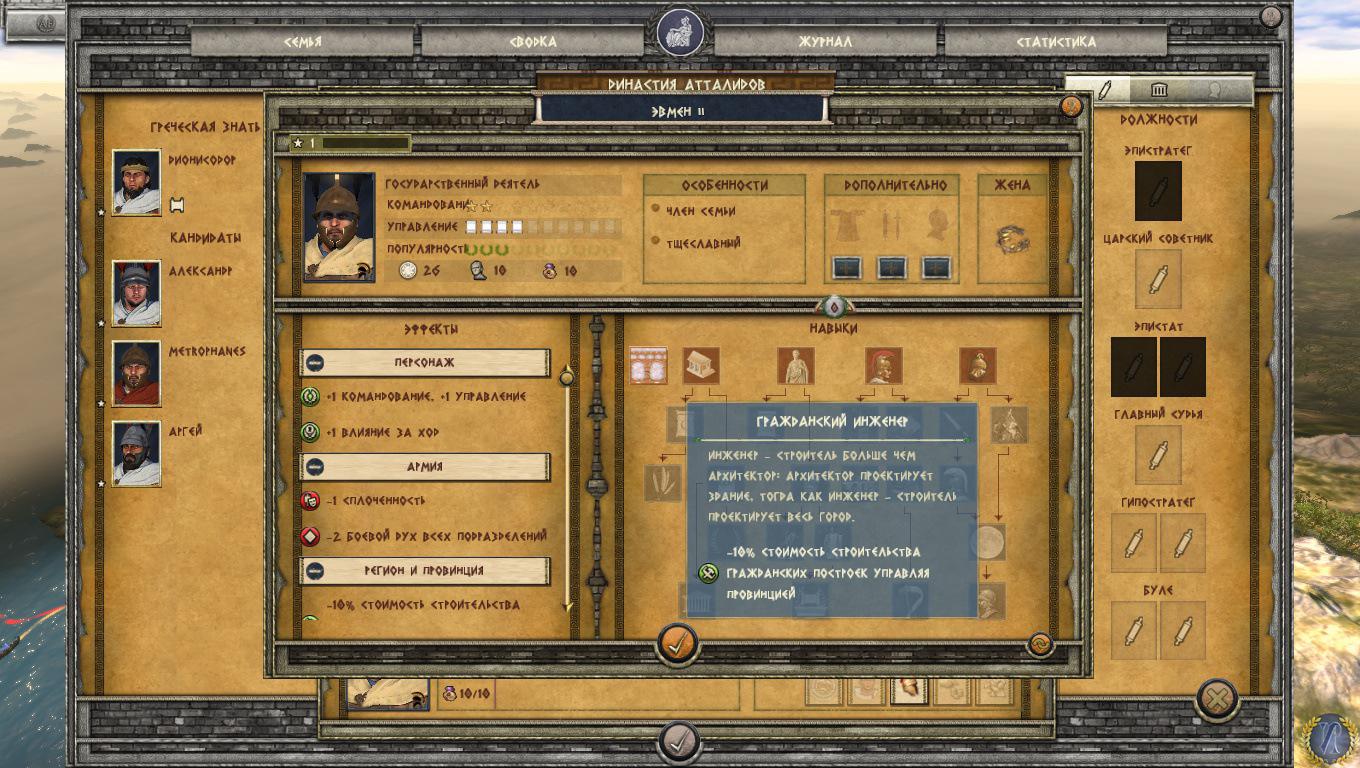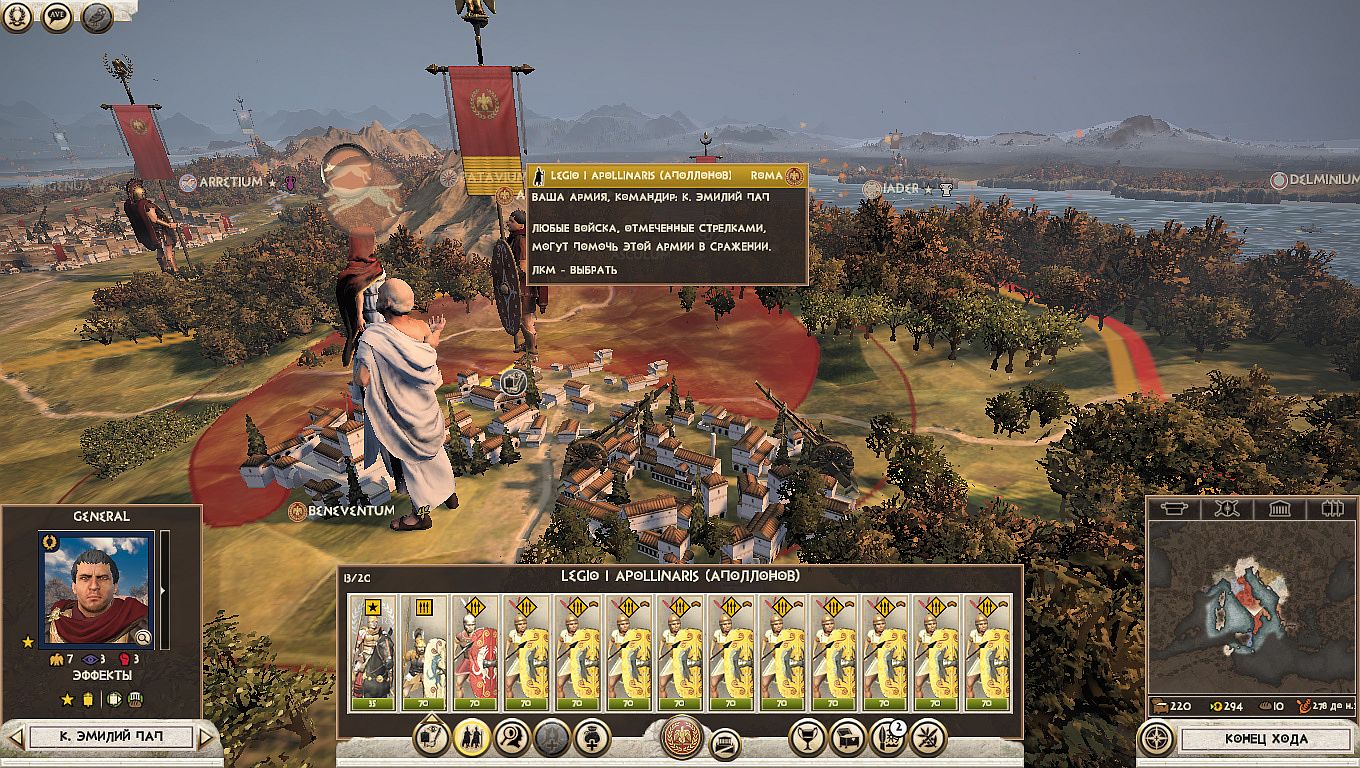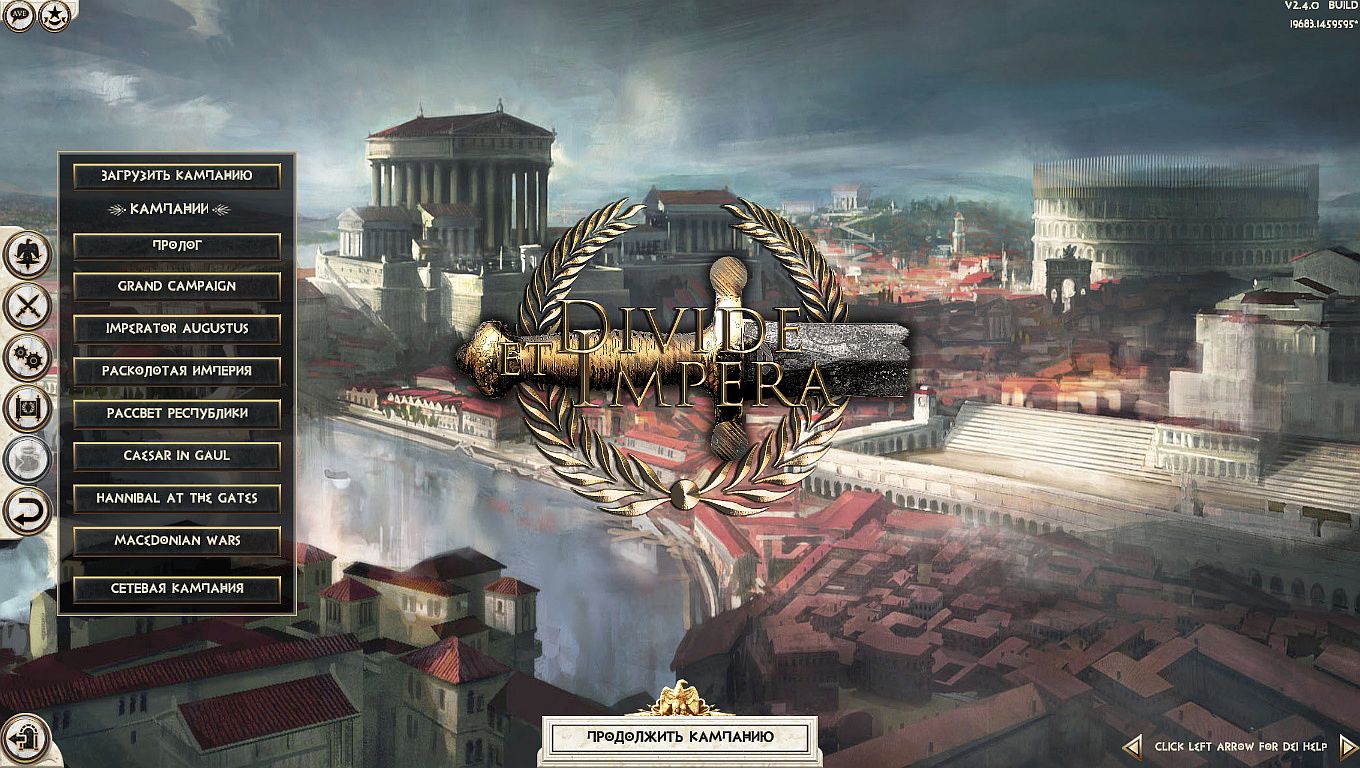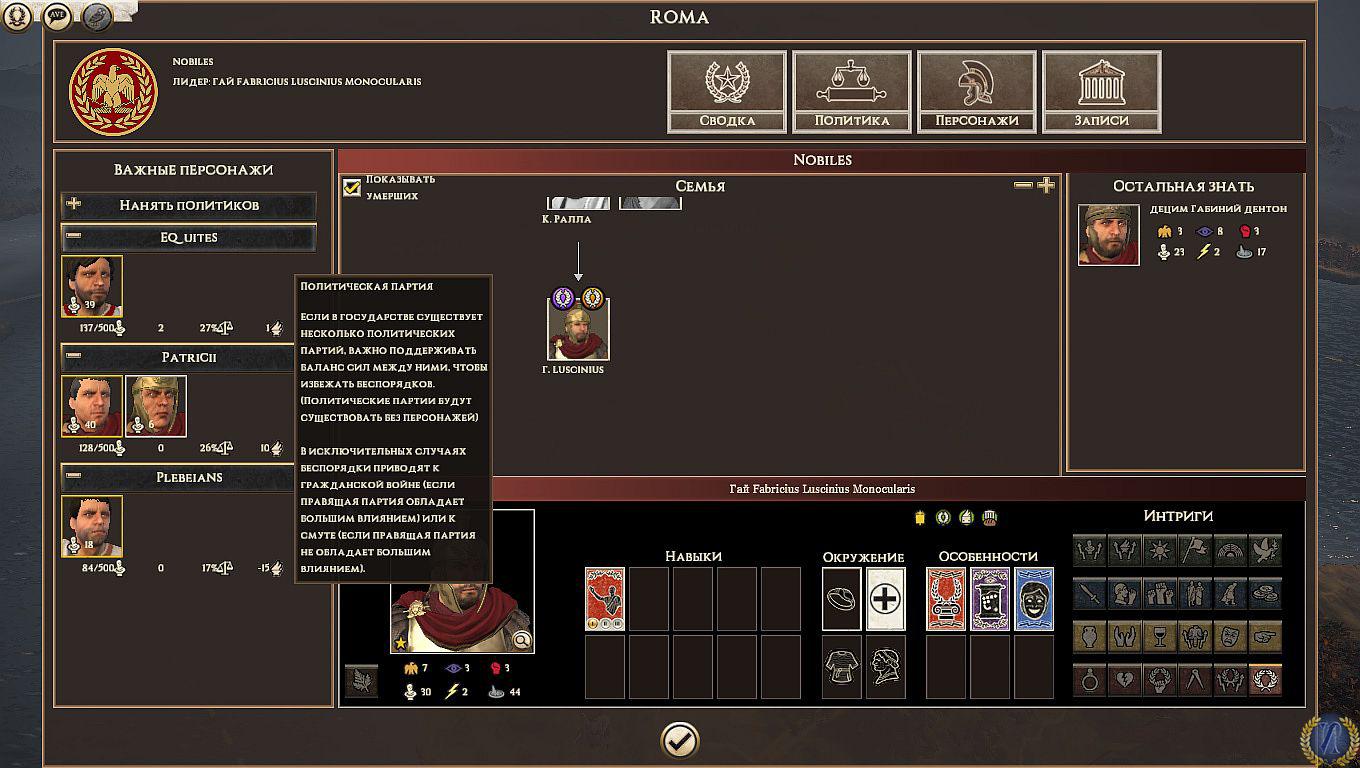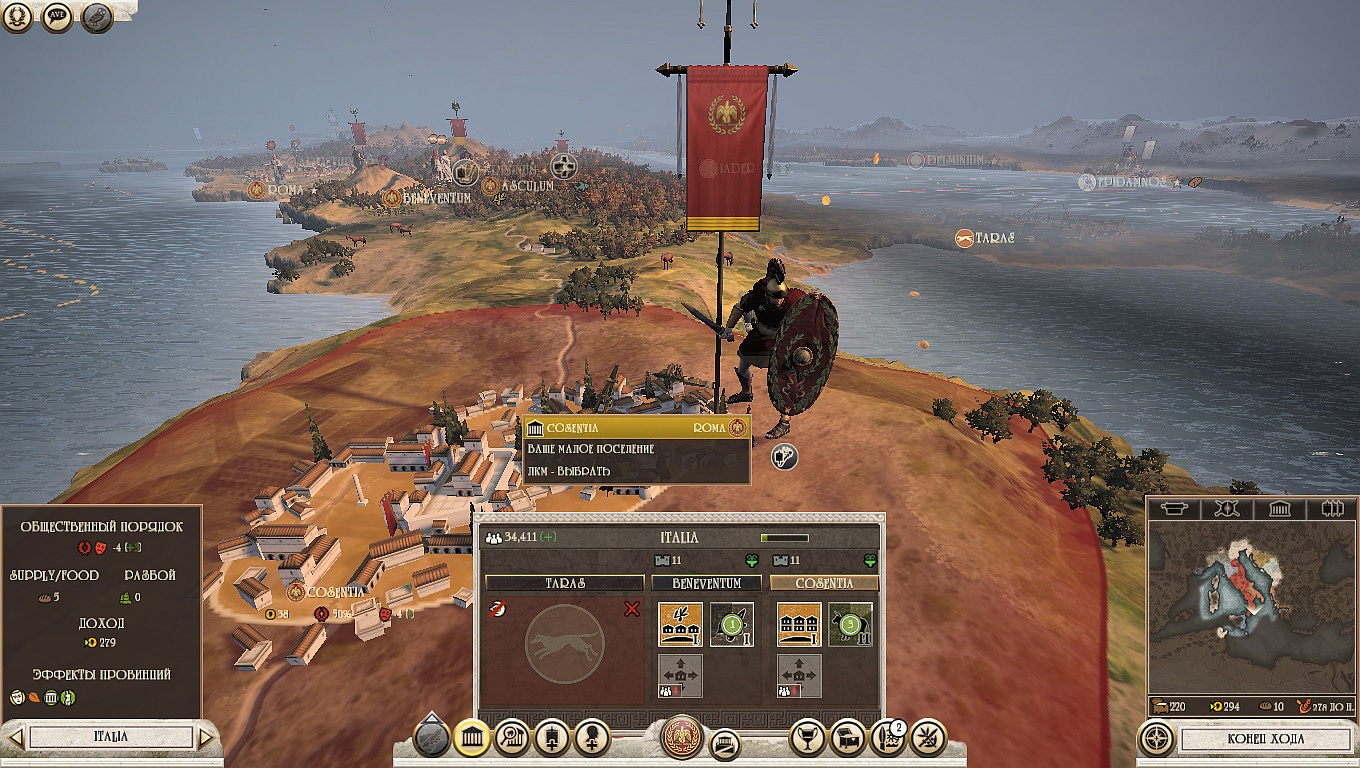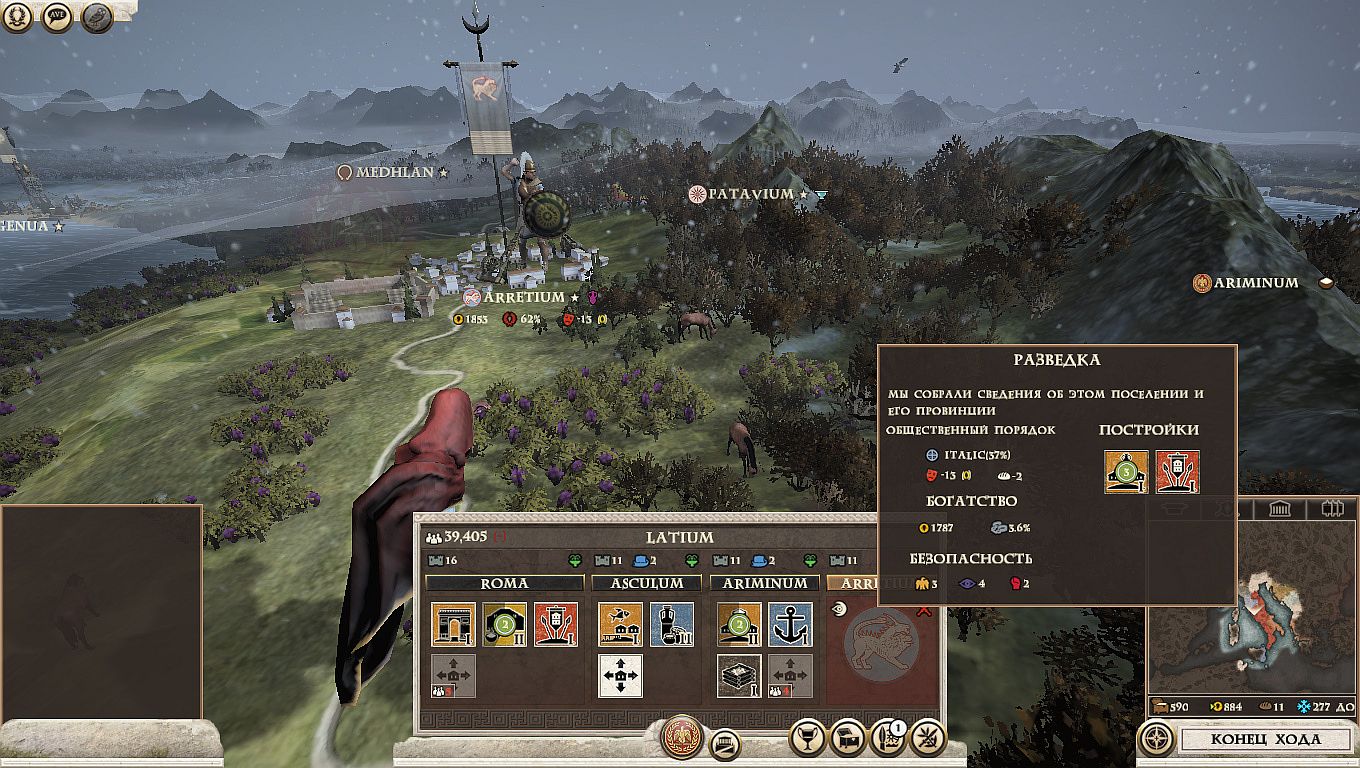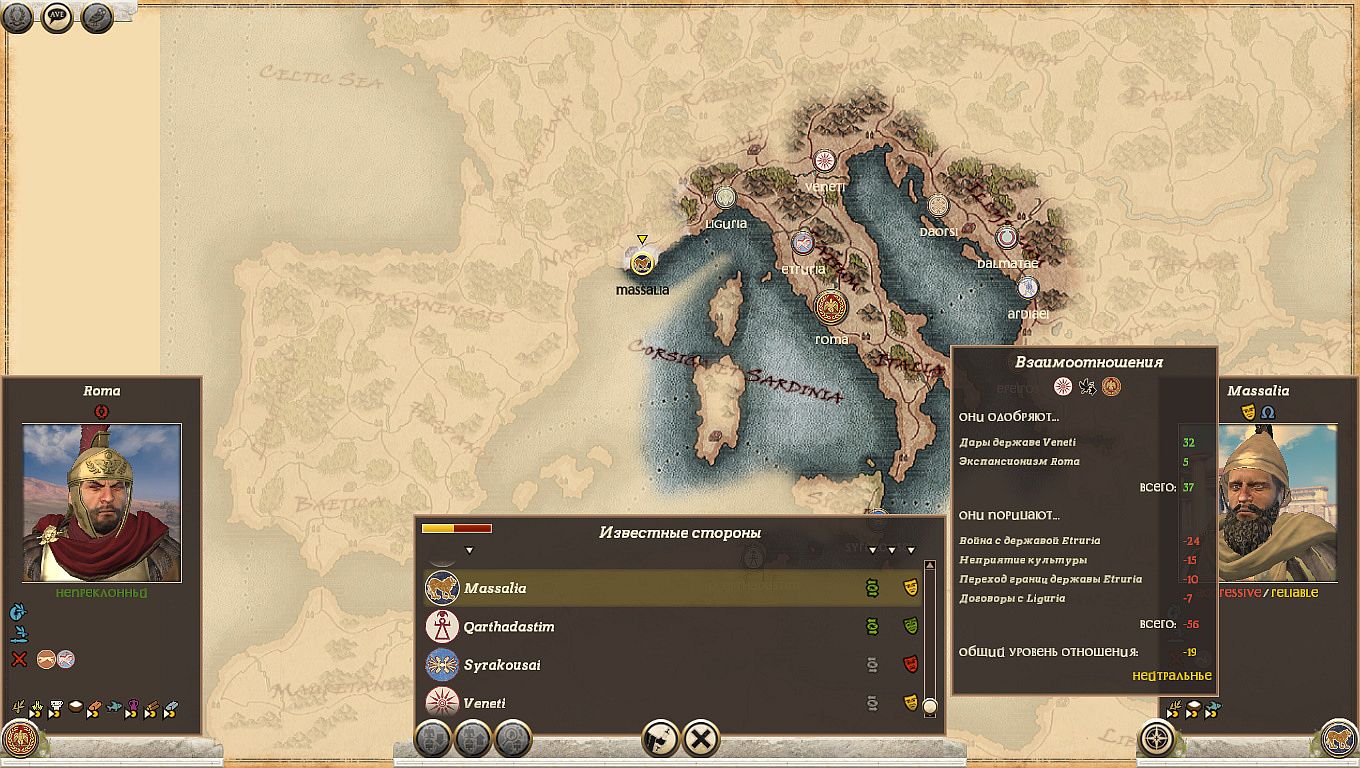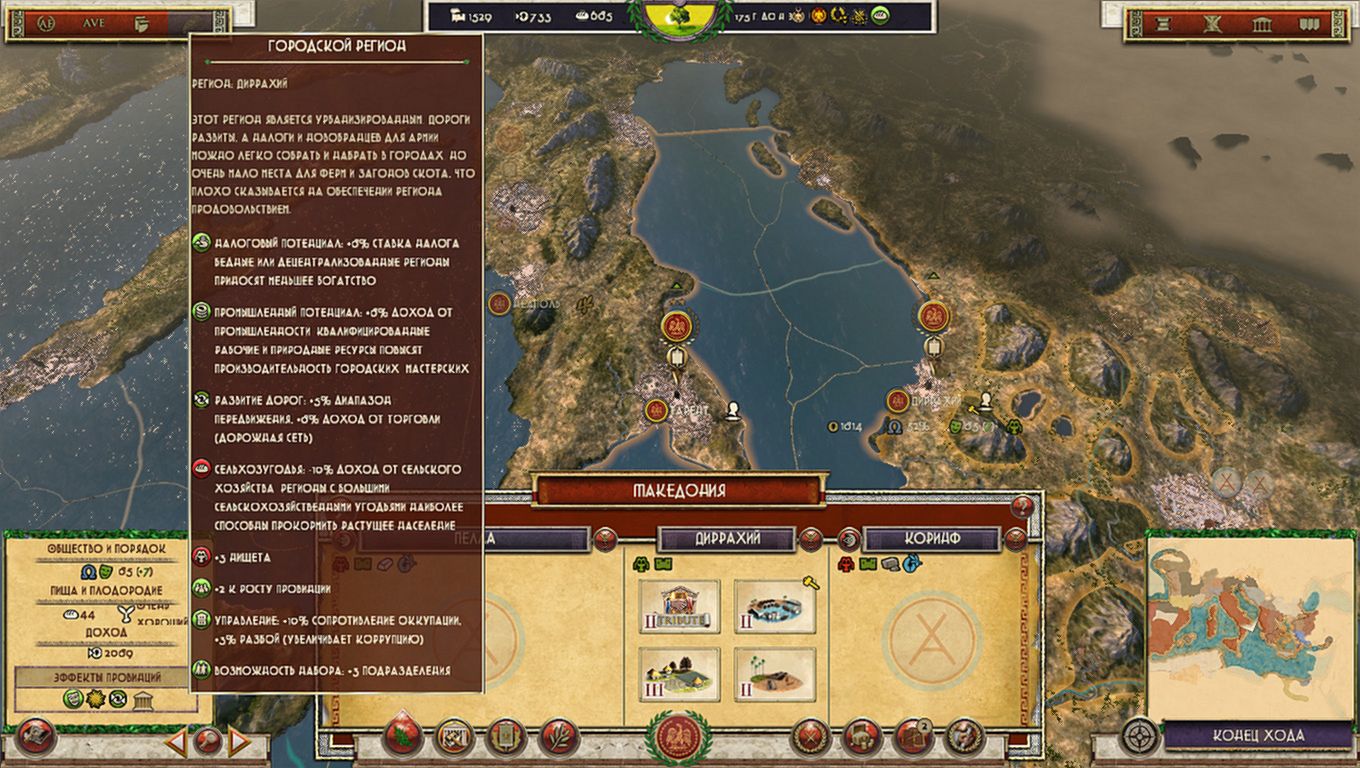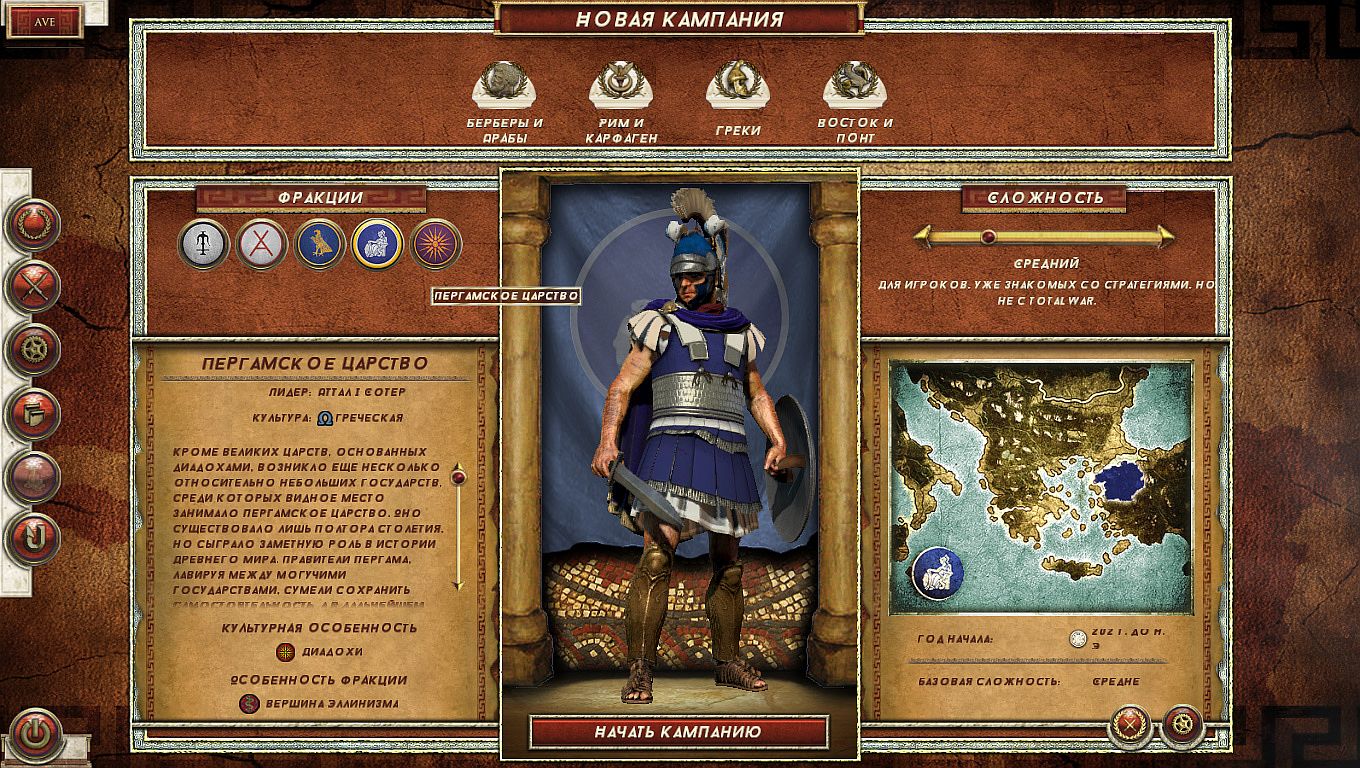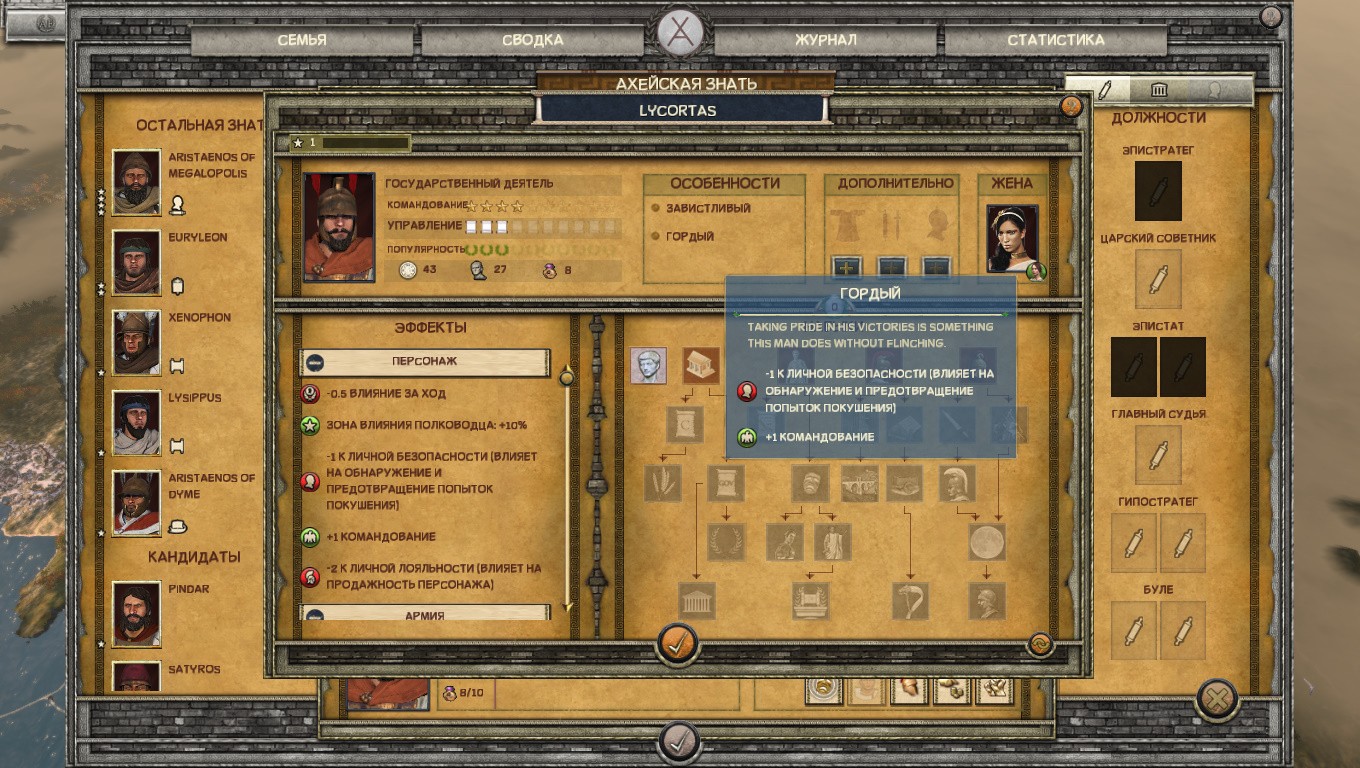
Универсальные шрифты для Total War: Rome II
Шрифты для ATW и TWR2. Можно использовать в качестве саб-модов
Саб-моды на шрифты изготовлены мной и идентичных не существует. То есть этот проект - детище "Империала".
На вопросы, подобные, таким как: сделай шире-уже, выше-ниже, и так далее, отвечу заранее и больше не буду, так как, ответ один - на данный момент возможности инструментария и не желание СА, ограничивают возможность делать вещи. Перед вами самые оптимальные варианты. Пока так. По мере возможности, постараюсь, что-то добавлять... По остальным вопросам - пожалуйста.
Греческий:
Римский:
Готический:
Выглядит отлично! :006:
Римский даже не пробовал, слишком простенький и не примечательный ничем ИМХО. А вот греческий просто отпад!!! При чем в самой игре он еще круче смотрится чем на скринах. Если на скринах изначально показалось что шрифт слабо читаемый, то это не так, в самой игре он намного разборчивей выглядит чем на картинках. Бабайцу зачет)))) :008: :006:
Просто супер!
То есть вы освоили этот нечеловеческий формат сайцев cuf? Если так, то, может быть, сделать мод, где у всех городов на карте будут историчные названия, написанные их письменностью? С греческими и римскими городами просто, это можно сделать на уже имеющемся материале, основная проблема с восточными городами. Их названия надо писать арамейским письмом, выглядит как иврит. Написать названия и даже шрифт я могу, а вот дальше я сделать уже не смог. Ну то есть я писал, делал, греческий шрифт свободно отражается в игре, а если написать по-арамейски, то будет просто пустота, т.к. нет соответствующего файла cuf. А для того, чтобы его создать, как я понял, надо освоить Java. Кроме восточных городов, кельтские и германские города можно сделать руникой. Руники везде полно.
Дело в том что, это, не реально скорее всего... Используемый шрифт игра берёт, как, слепой человек - по памяти(дали команду - рука потянулась к нужной коробочке. Другая команда - другая коробочка. Как, я понимаю - на уровне скриптов(?)...). То есть - шрифт один для всех написаний текста в игре. Думаю - можно и два использовать(простой и курсив), как, в "Тронах"... Но я до этого ещё не докатился :0142: Пара дней всего, как, с этой головоломкой разобрался - cuf.
Хотя попробовать... :038: можно было бы... А на карте надписи на родном(не адаптированном под кириллицу)?
תרבות יידיש(пример) - если знаешь то поймёшь, а если нет,то... А на кириллице такого нет,наверняка. :046:
P\S Да! И текстовики игры не имеют никакого отношения к шрифтам !!!! То есть - в текстовеке пиши хоть на марсианском, а, на мониторе будет отображаться выбранный саб-модом шрифт. Так что - вряд ли, что то, выгорит...
Супер камрад! Давно хотелось моды на шрифт на кириллице, а то только один и был, типа курсива. Шикарные шрифты :046: А то нужно порой менять что-то, приедается. Есть один чел в стиме, шрифты деалет, описание на русском было, я подумал ну круто, шрифты классные, а они на инглише только отображались. Вот Для просмотра ссылки Зарегистрируйтесь мод. Прям праздник завезли :006:
Не вижу ничего интересного в этом шрихте. Чем он лучше ванилы?! Если уж и менять, то на что то действительно оригинальное ИМХО
А менять лишь бы как говорят у нас - "Абы було", нафиг надо.
Вот я понимаю шрифт греческий, так это действительно интересно.
Не вижу ничего интересного в этом шрихте. Чем он лучше ванилы?! Если уж и менять, то на что то действительно оригинальное ИМХО
С ним лучше и чётче видно. Если и так всё хорошо с чёткостью, то разницы может и не быть, а мне хорошо видно